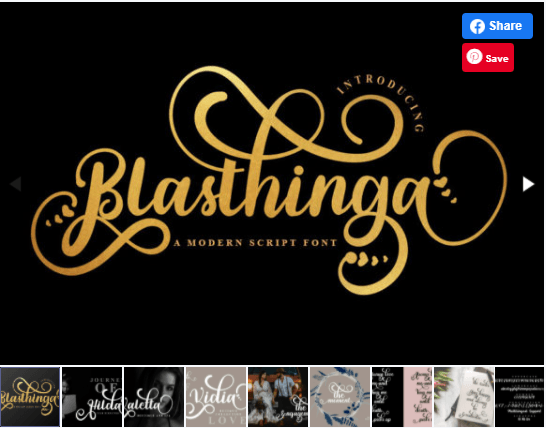
Blasthinga Font
Blasthinga a - это великолепный и смелый рукописный шрифт, созданный для придания стильности вашим заголовкам и проектам логотипов. Этот шрифт выглядит сильным, уверенным и динамичным и может добавить ностальгический характер вашим дизайнам. Этот шрифт закодирован в кодировке PUA, что означает, что вы можете легко получить доступ ко всем глифам и штрихам!